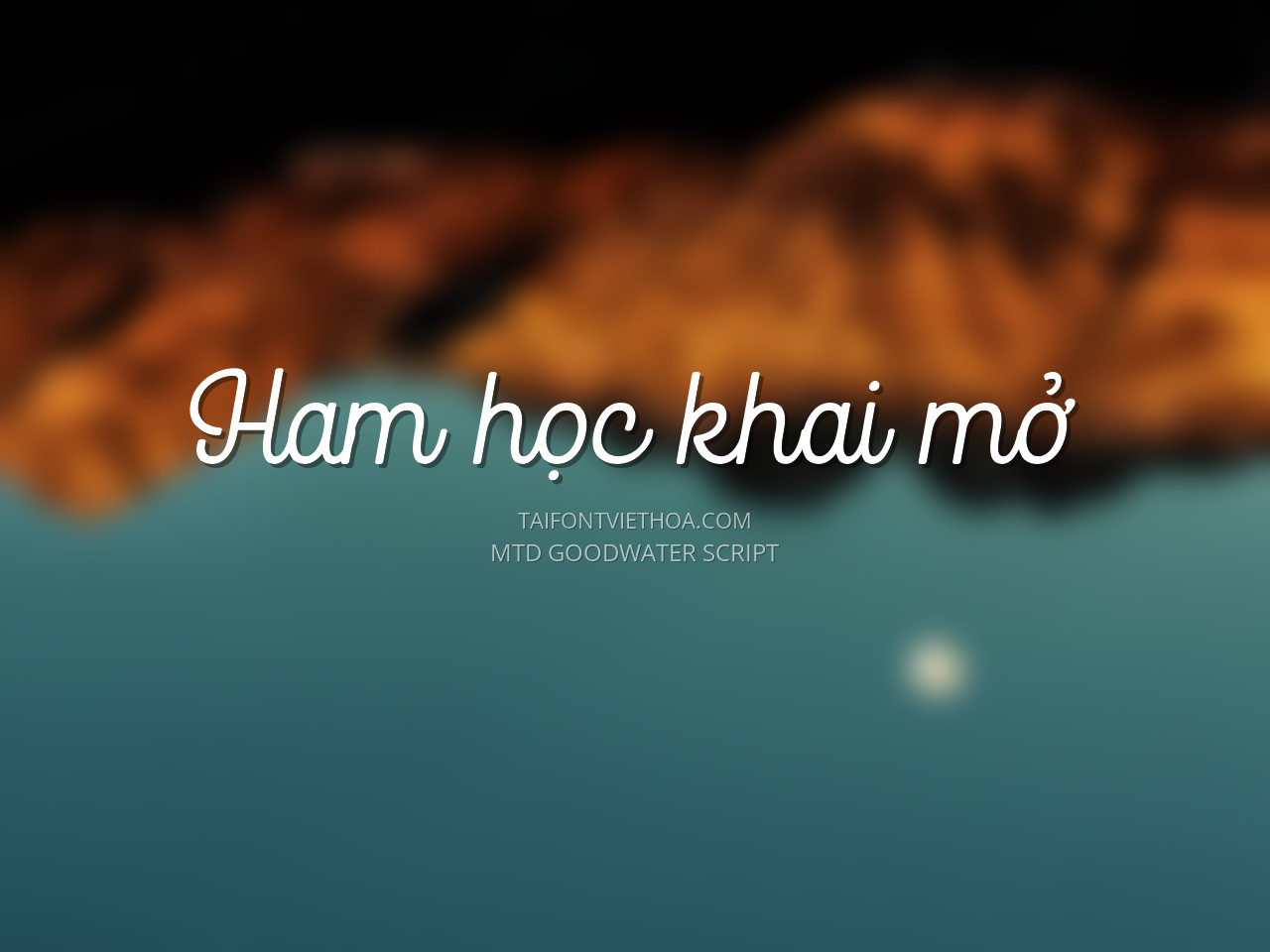
Font việt hóa MTD Goodwater
Giới thiệu về font Goodwater
Goodwater là một font chữ viết tay (handwritten script) mang phong cách tự nhiên và nhẹ nhàng, được thiết kế bởi Motokiwo Type (MTD). Font lấy cảm hứng từ những nét viết tay thường nhật, hòa quyện cùng sự mềm mại và nhịp điệu uyển chuyển trong từng chữ cái. Các đường nét của Goodwater không quá kiểu cách, mang lại cảm giác gần gũi, dễ chịu, đặc biệt phù hợp cho các thiết kế cá nhân hóa hoặc mang yếu tố cảm xúc. Phiên bản Việt hóa được thực hiện bởi chính MTD, hỗ trợ đầy đủ tiếng Việt và hơn 70 ngôn ngữ quốc tế, giúp font có thể sử dụng hiệu quả trong mọi môi trường thiết kế hiện đại.
Đặc điểm thiết kế và ứng dụng của font Goodwater
Goodwater có thiết kế mảnh nhẹ, hơi nghiêng, với các liên kết chữ mềm mại tạo cảm giác trôi chảy và mượt mà. Font được trang bị các ligatures và ký tự thay thế (alternates) giúp người dùng linh hoạt sáng tạo khi trình bày. Độ tương phản nhẹ giữa các nét tạo nên sự tinh tế, phù hợp cho các thiết kế đòi hỏi tính thẩm mỹ nhẹ nhàng.
Ứng dụng lý tưởng: thiệp cưới, tiêu đề blog cá nhân, bài đăng mạng xã hội, bao bì sản phẩm thủ công, quà tặng cá nhân, poster nghệ thuật và các thiết kế lifestyle mang phong cách gần gũi, nhẹ nhàng. Ngành nghề phù hợp: wedding planner, sáng tạo nội dung, giáo dục, thời trang nữ, studio ảnh, spa và các thương hiệu truyền cảm hứng hoặc thiên về cảm xúc cá nhân hóa.